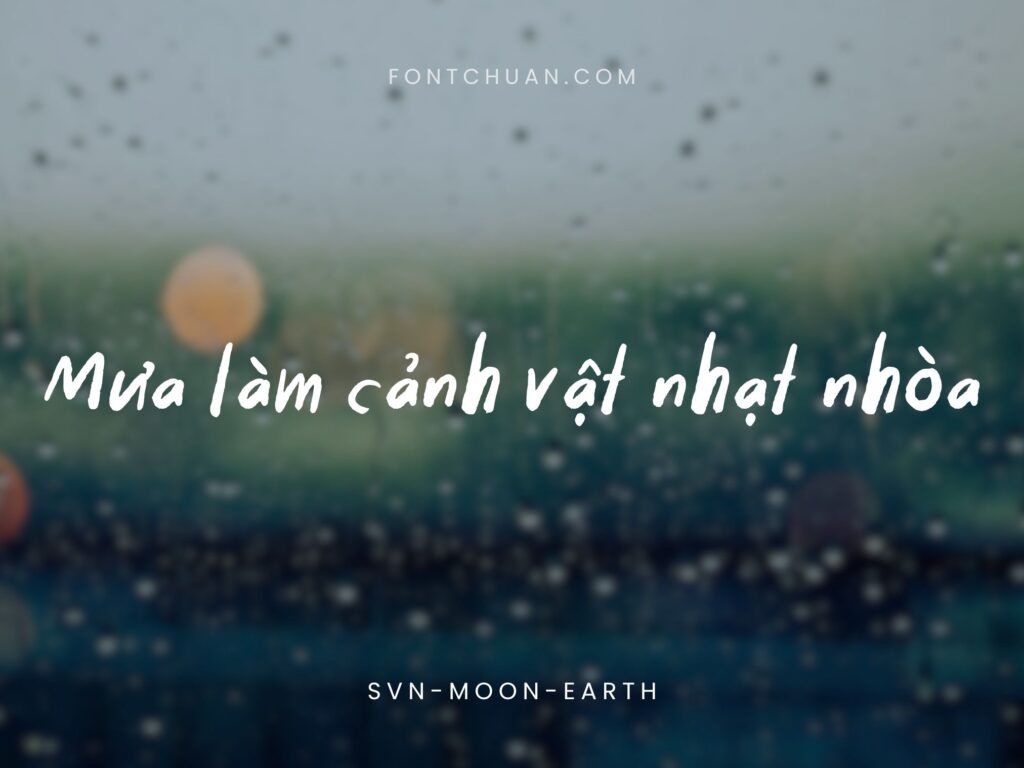
Font SVN Moon Earth Việt Hóa
Tác giả Font: Lia Wijayanti
Font SVN Moon Earth là phiên bản Việt hóa của kiểu chữ Moon Earth, được thực hiện bởi STYLEno.1 Fonts. Moon Earth là một kiểu chữ viết tay đơn giản và ấm cúng, được thiết kế bởi Lia Ari Wijayanti từ Orenari. Font này được viết tự nhiên bằng tay, tạo nên sự độc đáo và cá tính cho từng ký tự. Moon Earth bao gồm đầy đủ các ký tự chữ hoa, chữ thường, chữ số và dấu câu, hỗ trợ đa ngôn ngữ. Font này phù hợp cho nhiều mục đích sử dụng khác nhau như thiết kế trích dẫn, logo, tiêu đề, bao bì sản phẩm và các ấn phẩm truyền thông.
Với phong cách mềm mại và gần gũi, SVN Moon Earth còn được xem là một Font chữ ẩm thực lý tưởng, giúp các thương hiệu nhà hàng, quán cà phê hoặc tiệm bánh thể hiện nét tự nhiên, ấm áp và thân thiện trong thiết kế menu, bảng hiệu hay bao bì sản phẩm. Ngoài ra, SVN Moon Earth vẫn lý tưởng cho các dự án thiết kế yêu cầu sự thân thiện và tự nhiên, như trích dẫn, logo thương hiệu và các ấn phẩm truyền thông. Các ngành nghề như giáo dục, ẩm thực và thiệp cưới có thể tận dụng font này để tạo điểm nhấn trong thiết kế. Font cũng thích hợp cho các sự kiện như Sinh nhật, Valentine, Tết và các lễ hội khác.